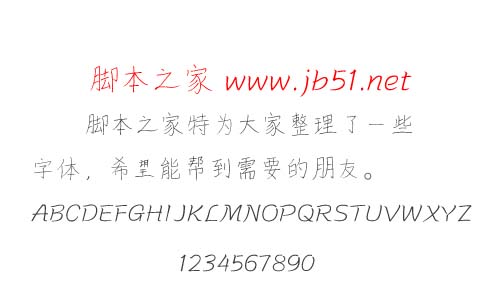
錢氏字體是一款比較細(xì)的用于手寫設(shè)計(jì)方面的卡通字體。該字體充滿童真,非常有趣,整體效果非常的出色,且字庫(kù)完整,可以廣泛應(yīng)用于廣告設(shè)計(jì)、宣傳海報(bào)、ppt、影視制作以及任何使用文字的領(lǐng)域,歡迎有喜歡或需要此字體的朋友們前來(lái)下載使用。